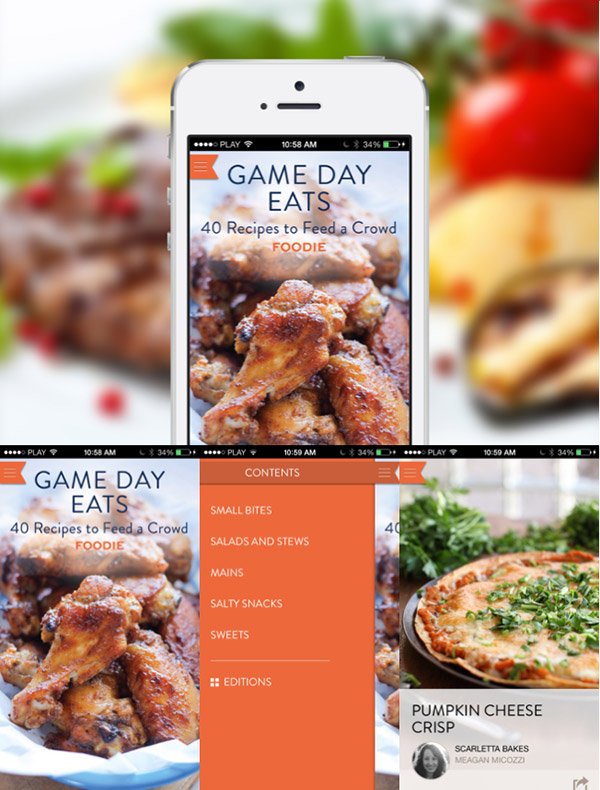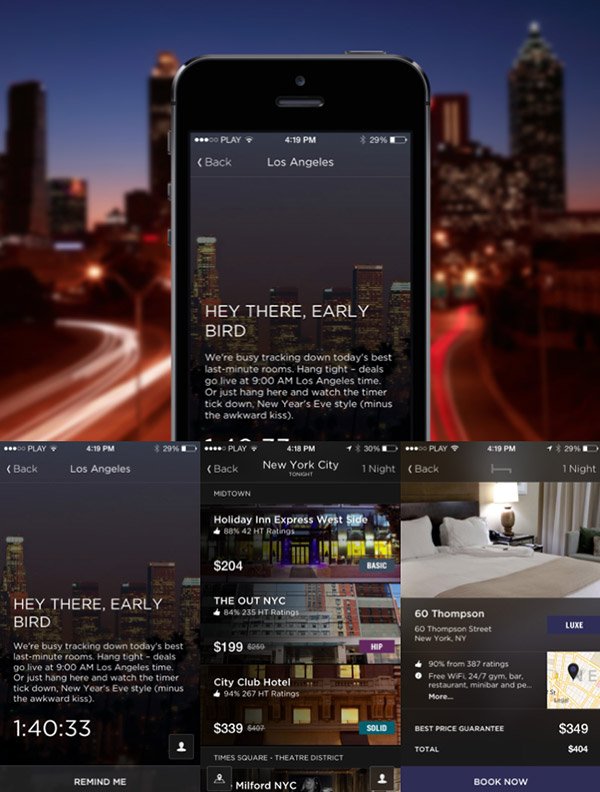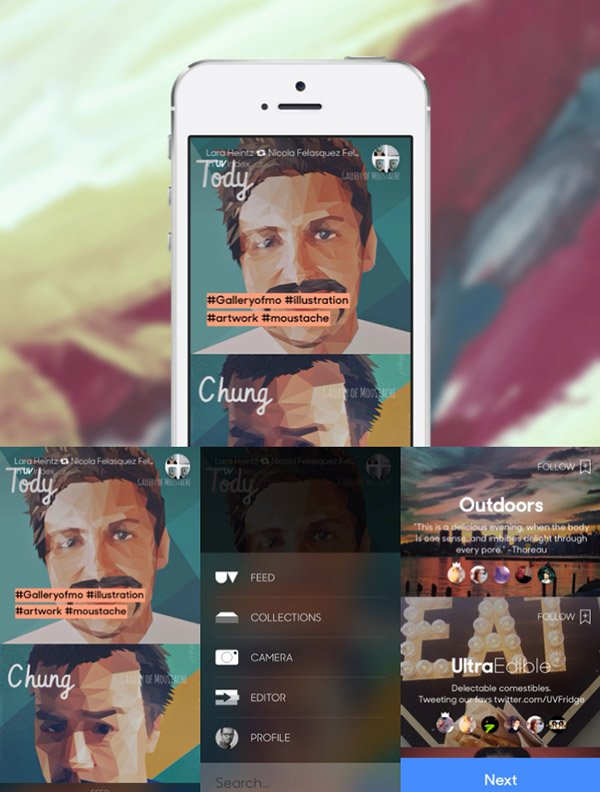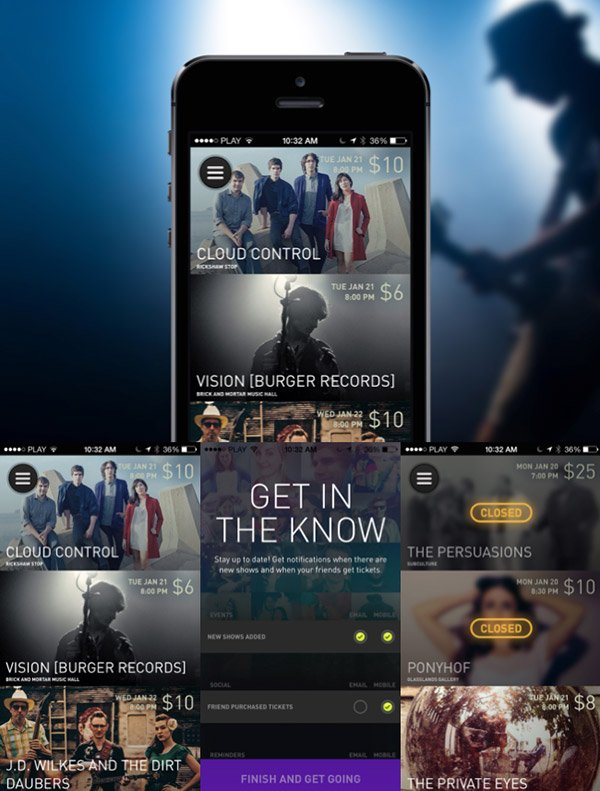
我有个小小的心得可以分享给你——好的字体等于成熟的设计。直至几年前,网页设计师们都还没有对字体表现出足够的关注。如今这个领域已日趋成熟——字体繁荣发展,成为一股巨大的设计潮流。
好的字体在文本的易读性上起了决定作用,却不止于此,它也传递出设计师分享的意图。它是整个用户体验的重要部分。从另一方面讲,缺乏好的字体,是整个产品不专业的表现。文字是主要界面的基础元素——如果它设计得很糟,为何还要深入下去?
本地应用第一年在iOS和Android平台上的发展,简直惨不忍睹。似乎大多设计师和开发者根本没有考虑过字体问题。它不受重视,显得很突兀。所用的那些令人生厌的字体毫无品味。真是一场设计的噩梦。
如今,移动端设计已经远远超越早期的水平,这个领域成熟的迹象已经显露。字体是它最形象的例子。主流应用中的大多字体可以用“得体”来形容。无论是Facebook、Mailbox或是Twitter——文字清晰,字体看上去至少还不错。更有趣的是——2013年,我们看到越来越多移动应用在字体的使用上,表现出了震撼的效果。Ultravisual、WillCall、Hotel tonight就是几个很棒的案例。
可以肯定的是,在2014年,这股趋势将会形成更加强大的力量。
不能再忽视APP中的字体了。移动端的设计已经成熟。
Citroen Lifestyle, iOS
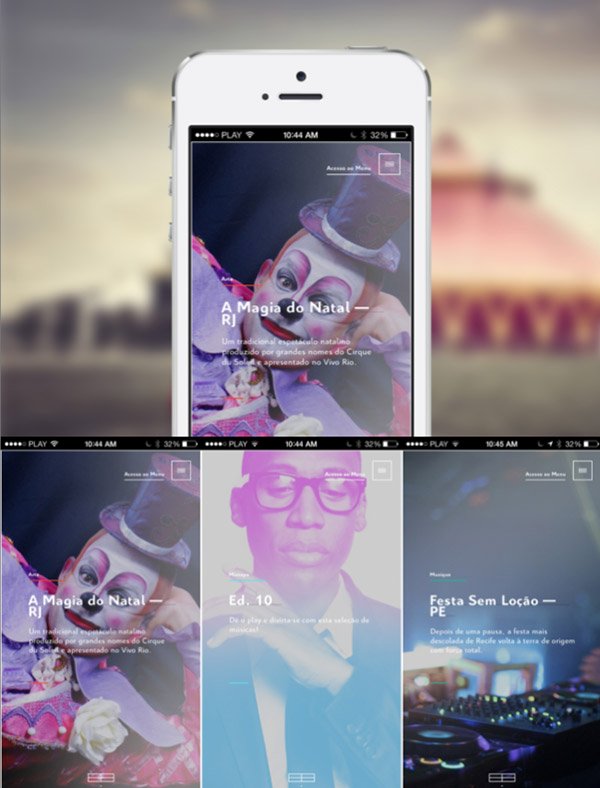
Fancred, iOS
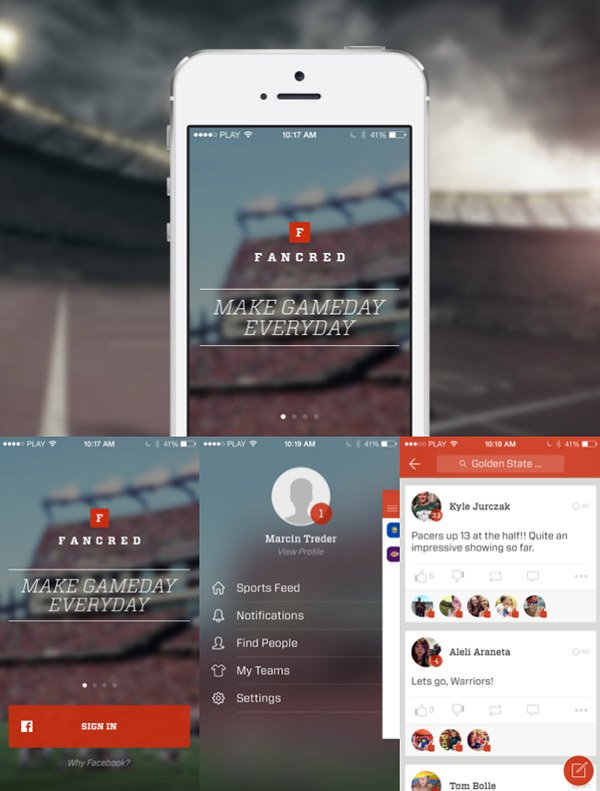
Fifa, iOS, Android
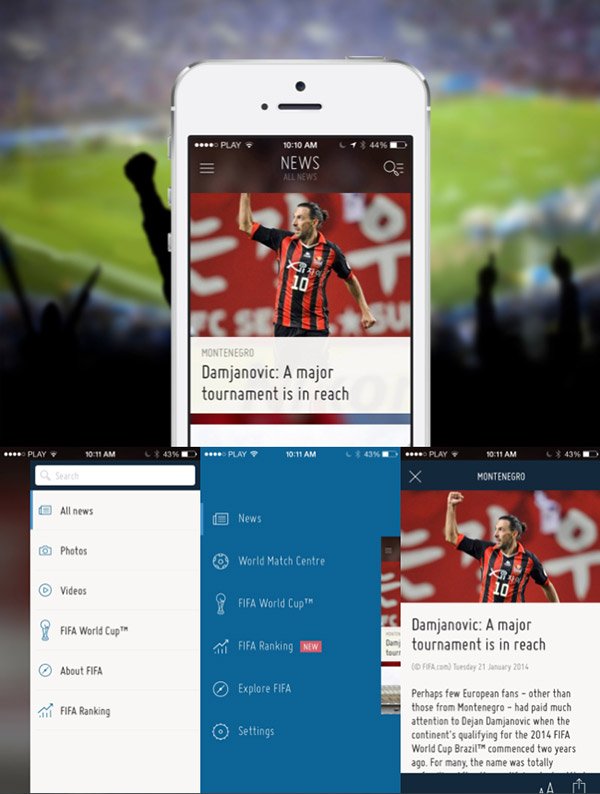
Foodie Recipes, iOS
Hotel Tonight, iOS, Android
National Geographic City Guide, iOS
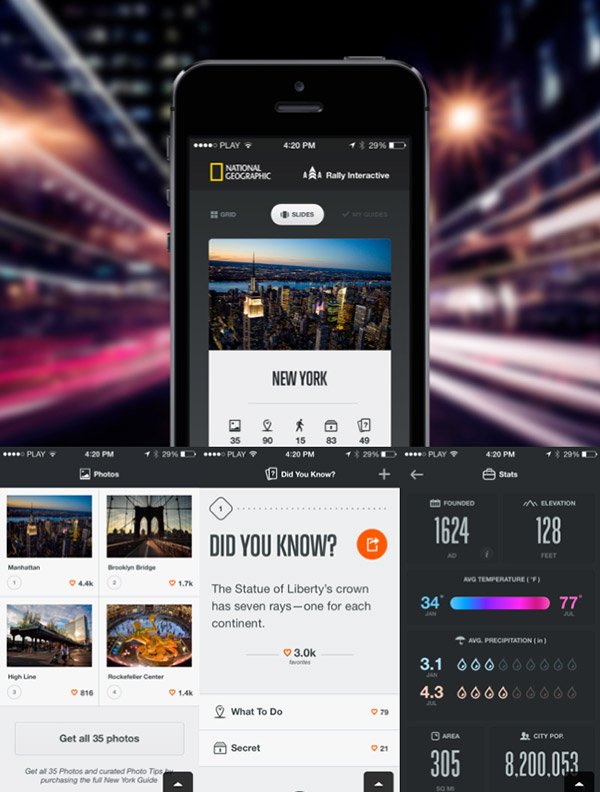
Ultravisual, iOS
Willcall, iOS, Android